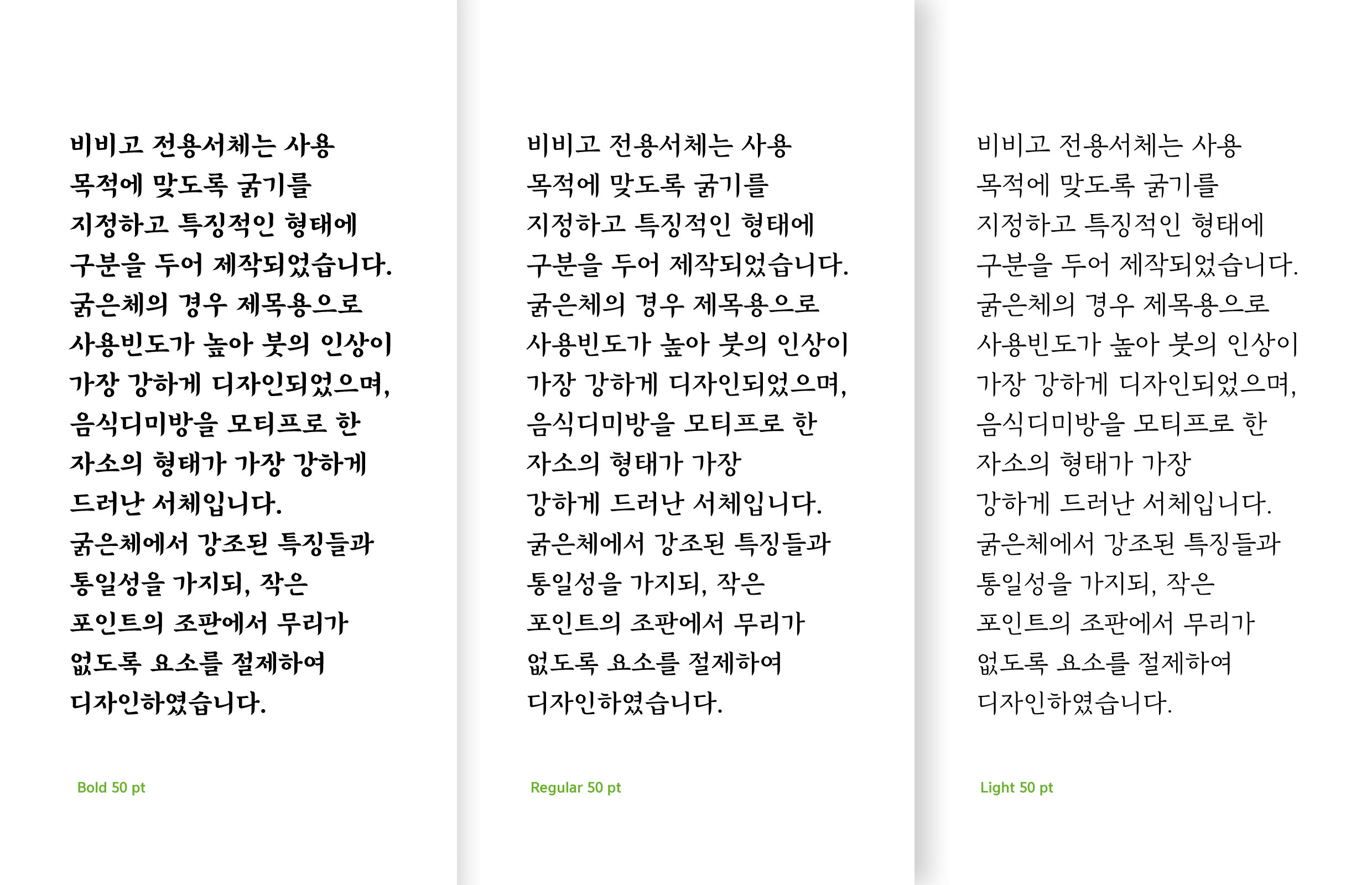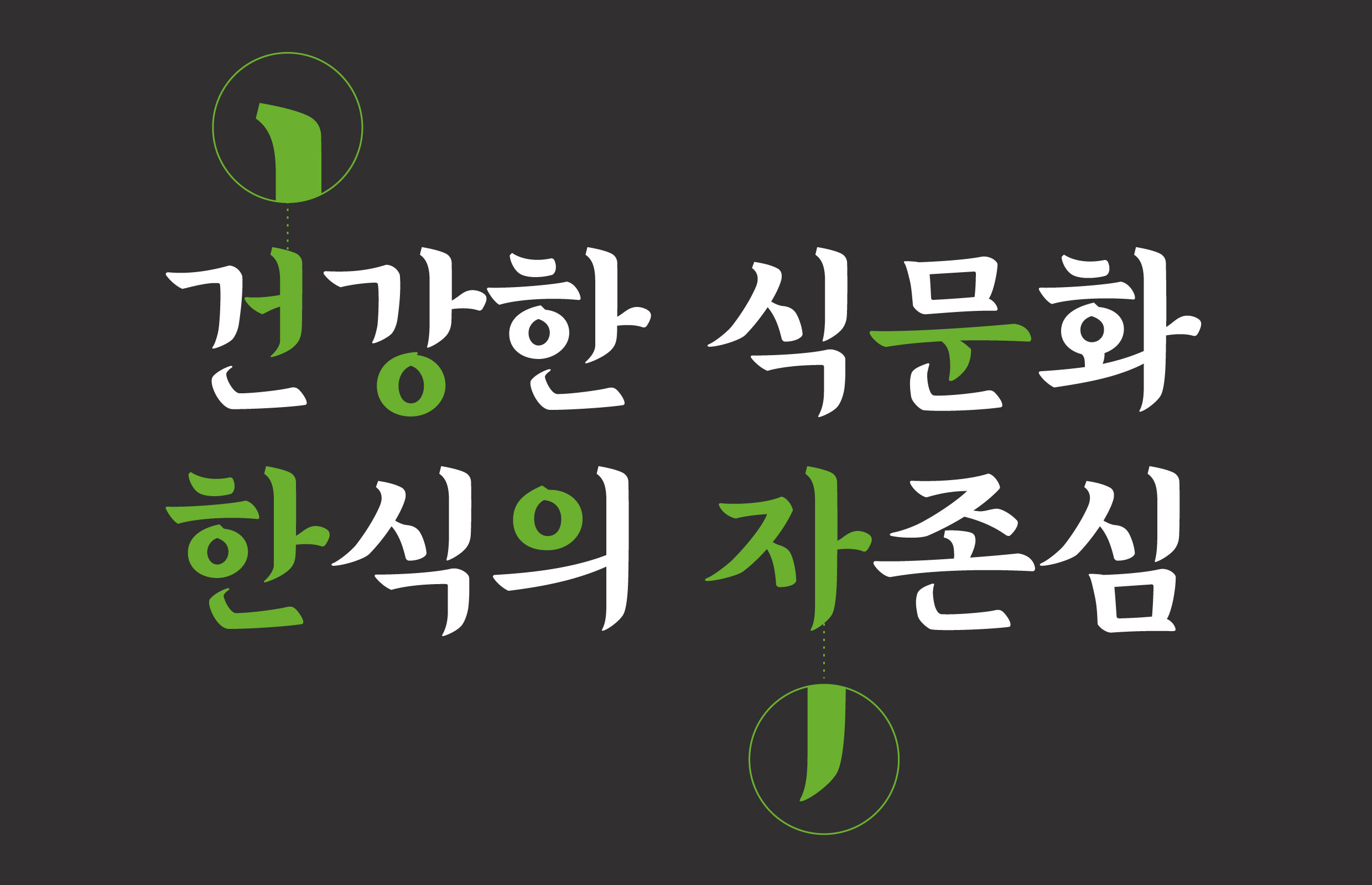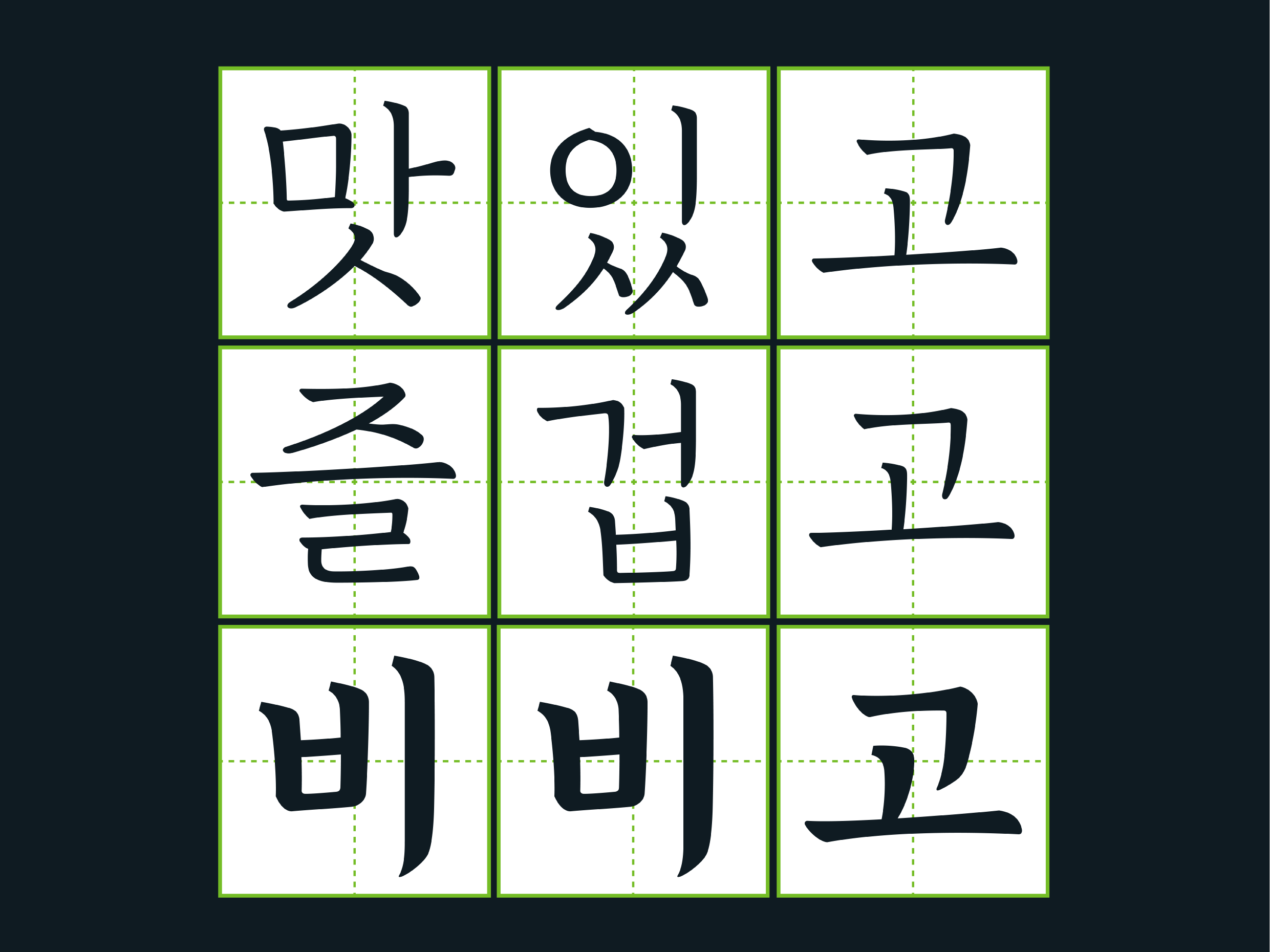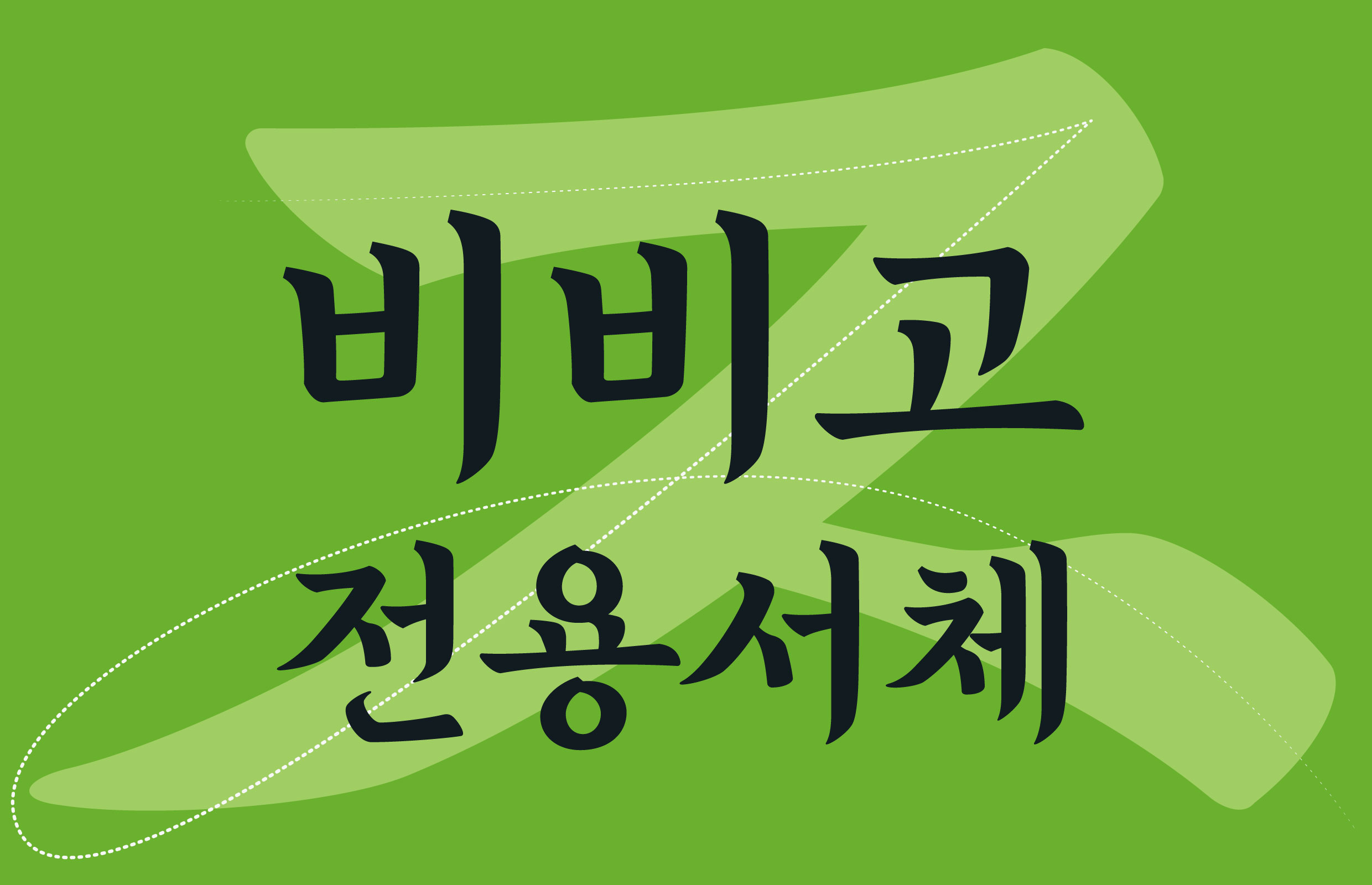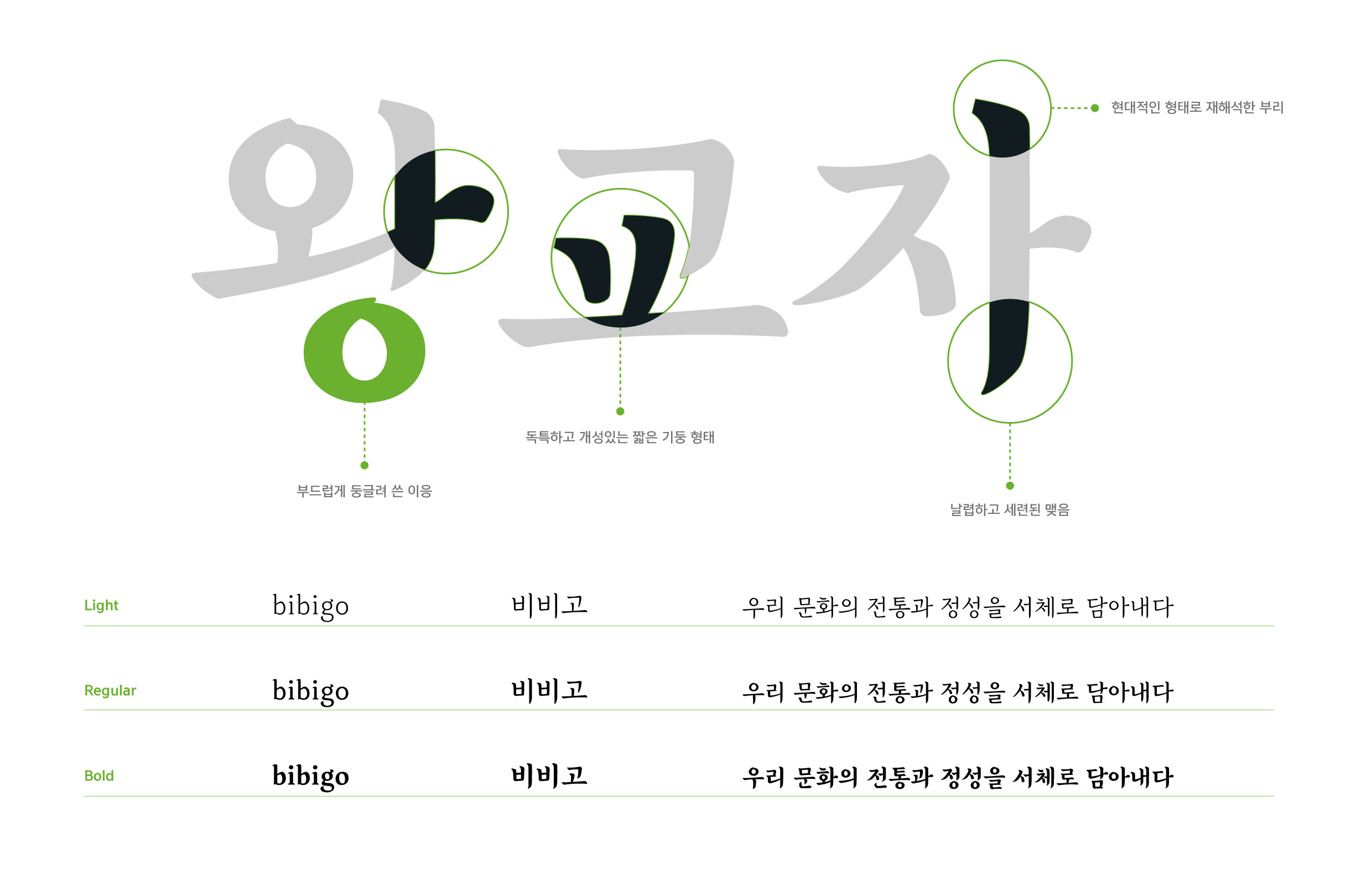
CJ제일제당 [비비고]
여성이 쓴 최초의 한글 조리서 (1670)에 나타난 섬세하고 유연한 필체를 현대적으로 재해석한 서체다. ‘한식’, ‘정성’, ‘전통과 현대의 균형’을 주요 테마로 삼았으며, 요리하는 이의 정성 깃든 손을 형상화하고자 곡선미가 도드라지는 손글씨로 제작했다.
CJ제일제당